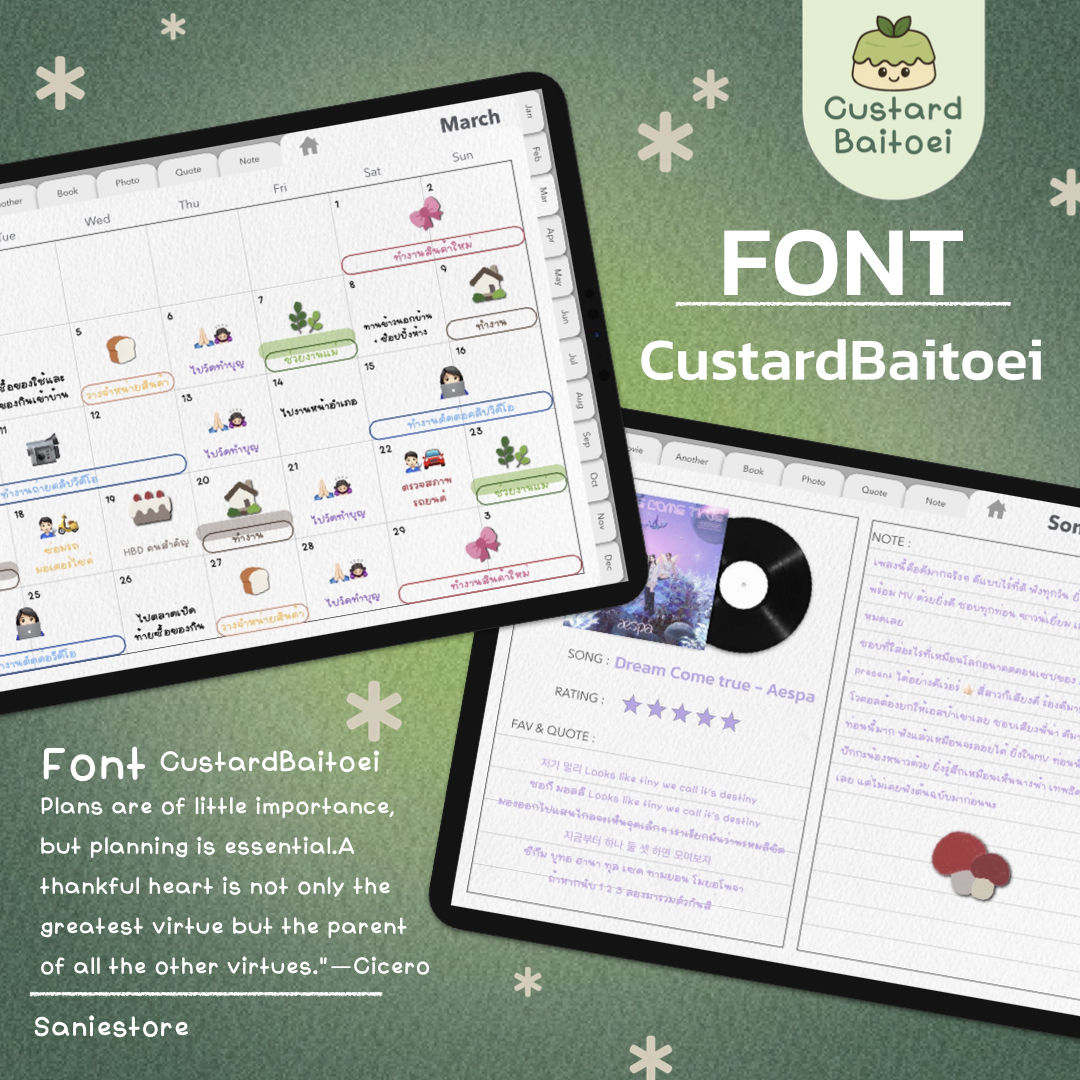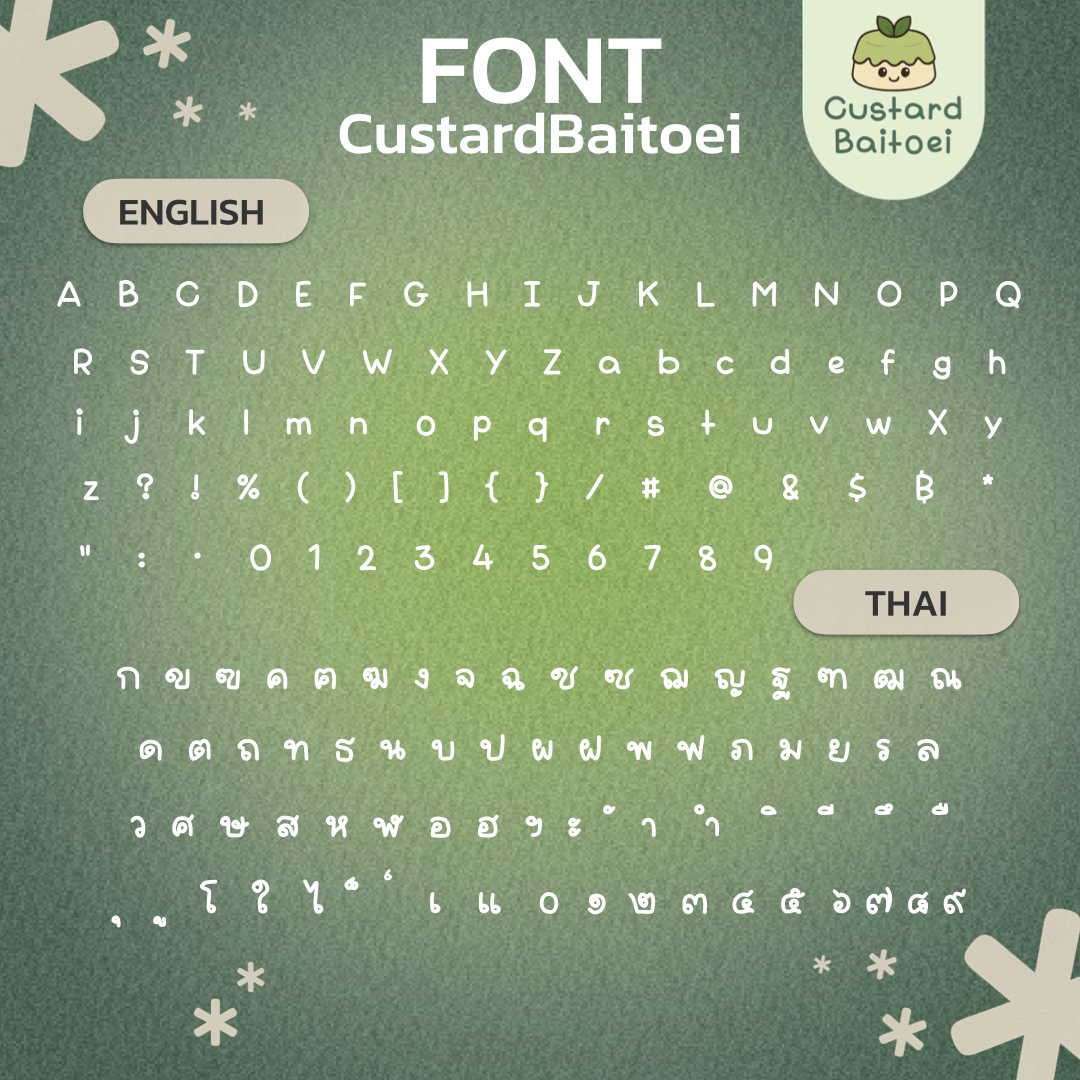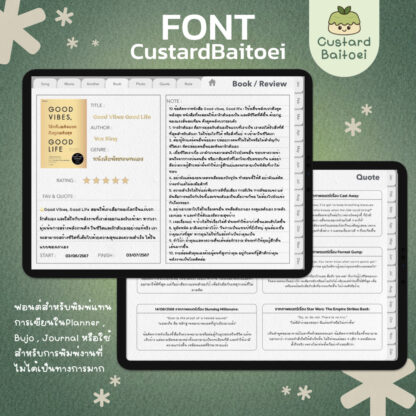
🌿𝐅𝐎𝐍𝐓 𝐂𝐮𝐬𝐭𝐚𝐫𝐝 𝐁𝐚𝐢𝐭𝐨𝐞𝐢 สำหรับส่วนตัว ฟอนต์คัสตาร์ดใบเตย
✨ เปิดตัวฟอนต์ใหม่สุดน่ารัก – CustardBaitoei นุ่มละมุนเหมือนคัสตาร์ดใบเตย 💚 เหมาะกับทุกคนที่รักการจดแพลน! พร้อมเสิร์ฟแล้ววันนี้!” 🍃📝 ใช้แล้วโน้ตดูน่าอ่านขึ้นอีก 100%
เหมาะกับ:
📅 เขียนตารางแพลนเนอร์
📚 ทำ bullet journal
🎧 จดโน้ตรีวิวเพลง / หนัง
📌 สร้างฟีลจดน่ารัก ๆ ไม่เบื่ออีกต่อไป!
🔤 รองรับภาษาไทย & อังกฤษ